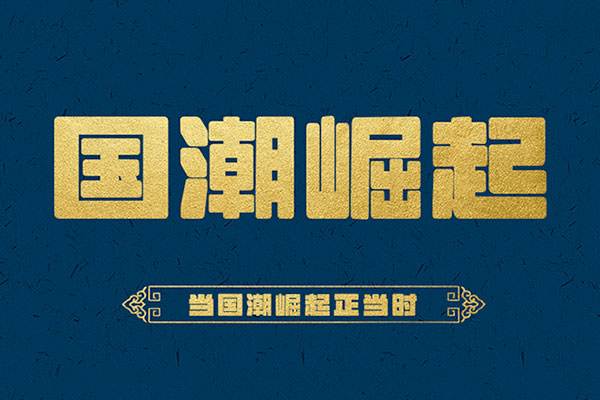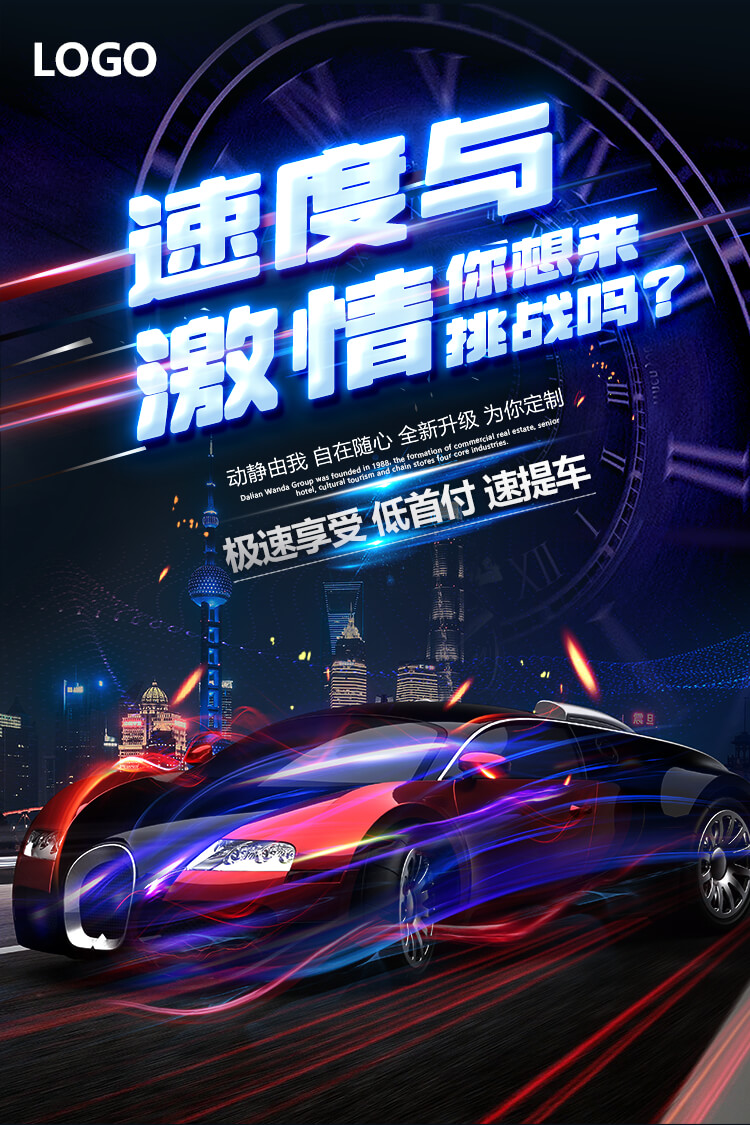
荆南缘默体
荆南缘默体,又名为Kingnamtype Rounded Sinoheadline Regular,是由中国大陆字体爱好者“皇帝的新冠”倾力打造的一款中文字体。据作者透露,初期的字体设计并非现在的圆角风格,而是在逐步完善的过程中逐渐加入了圆角元素,旨在为字体增添一抹趣味性,同时避免给人以过于刻板的圆体美术体印象。
荆南缘默体的应用场景非常广泛。无论是店招、房地产广告,还是地铁公交站广告海报,以及线上线下的各类产品宣传,甚至是个人VLOG封面标题。无论您是设计师还是普通用户,都会对这款字体的应用感到满意。
荆南缘默体包含了BG2312标准规定的6763个汉字,同时还涵盖了西文、数字、符号、日文平假名、日文片假名、注音符号和汉语拼音等多种字符。这意味着无论您需要排版哪种类型的文本,它都能够满足您的需求。
荆南缘默体效果预览
荆南缘默体字体效果预览